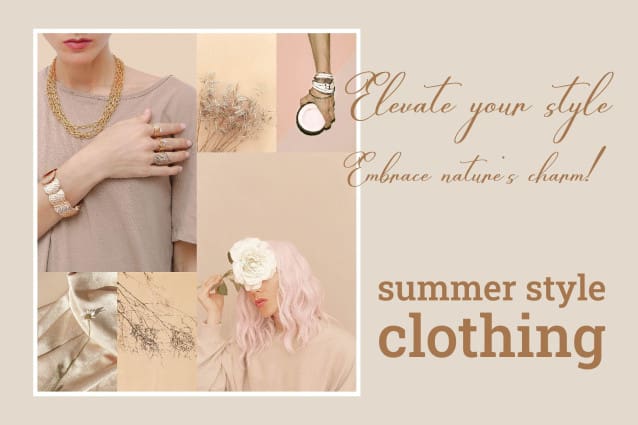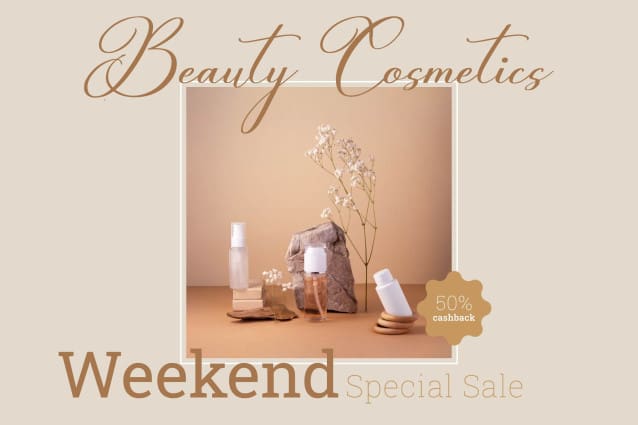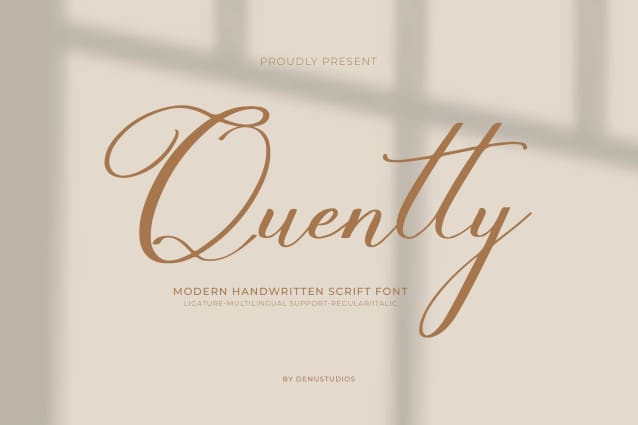
Quentty Script Font
Quentty Script Font, dari Gracetypestudio, cocok untuk proyek apa pun seperti: logo, proyek branding, desain peralatan rumah tangga, kemasan produk, mug, quotes, poster, tas belanja, kaos oblong, sampul buku, kartu nama, kartu undangan, kartu ucapan, label , fotografi, tanda air, acara khusus, dan semua proyek indah Anda lainnya yang memerlukan cita rasa naskah yang indah.